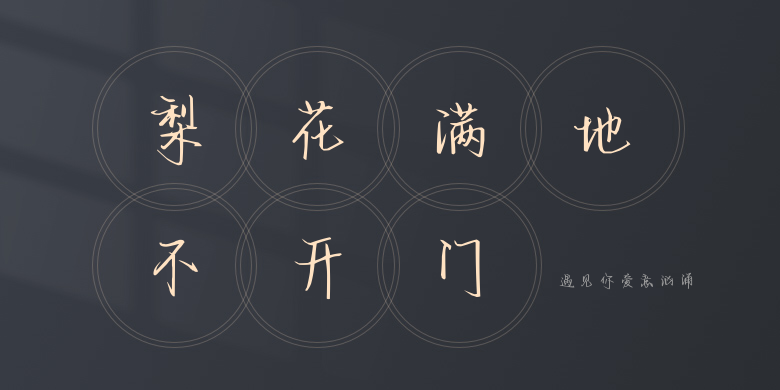
遇见你爱意汹涌
遇见你爱意汹涌,这款字体结构工整、笔画清晰,兼顾美观与易读性,适用于标题、正文、海报、包装、LOGO 等多种场景。字形优雅稳定,风格百搭耐看,适配日常排版与创意设计,让文字呈现更舒适、更具质感。遇见你爱意汹涌一笔一画,皆是细节,以均衡的比例、流畅的线条打造舒适视觉体验,字形端正大气,风格简约现代。无论是商业设计、品牌宣传还是日常排版,都能轻松驾驭,让文字更有格调与力量。遇见你爱意汹涌字体下载。